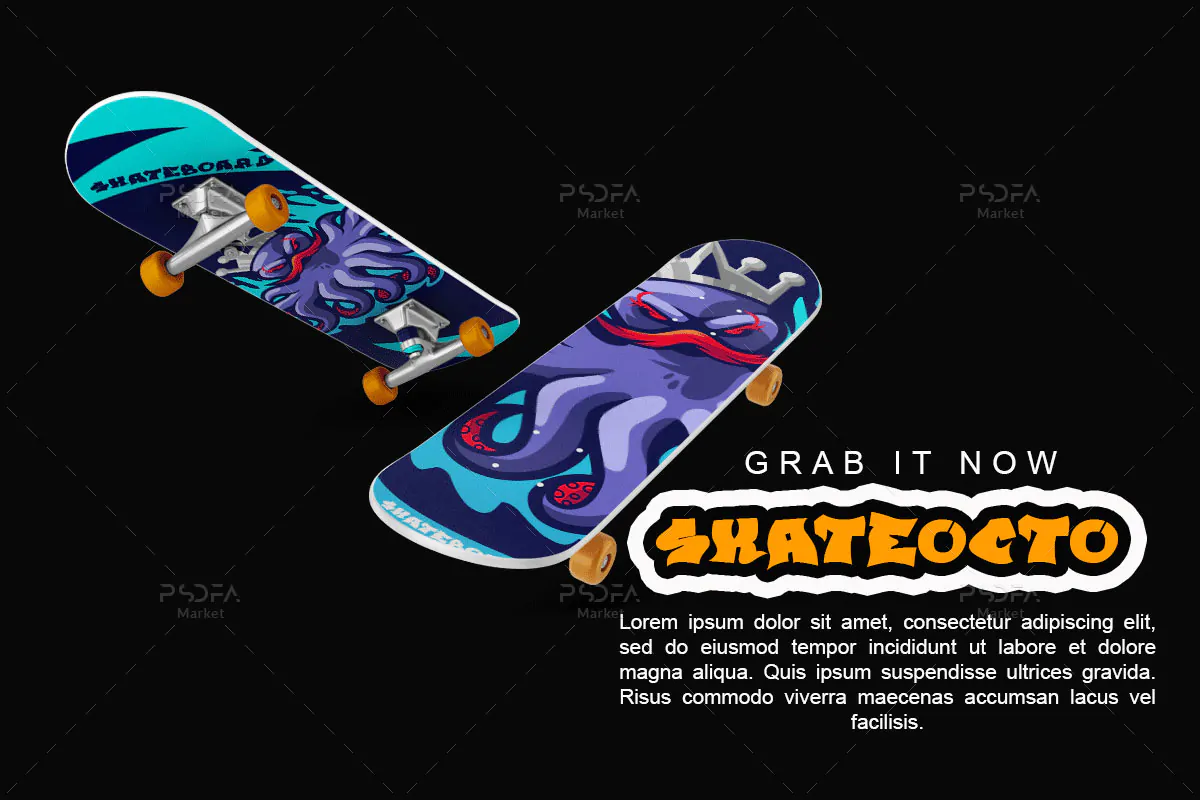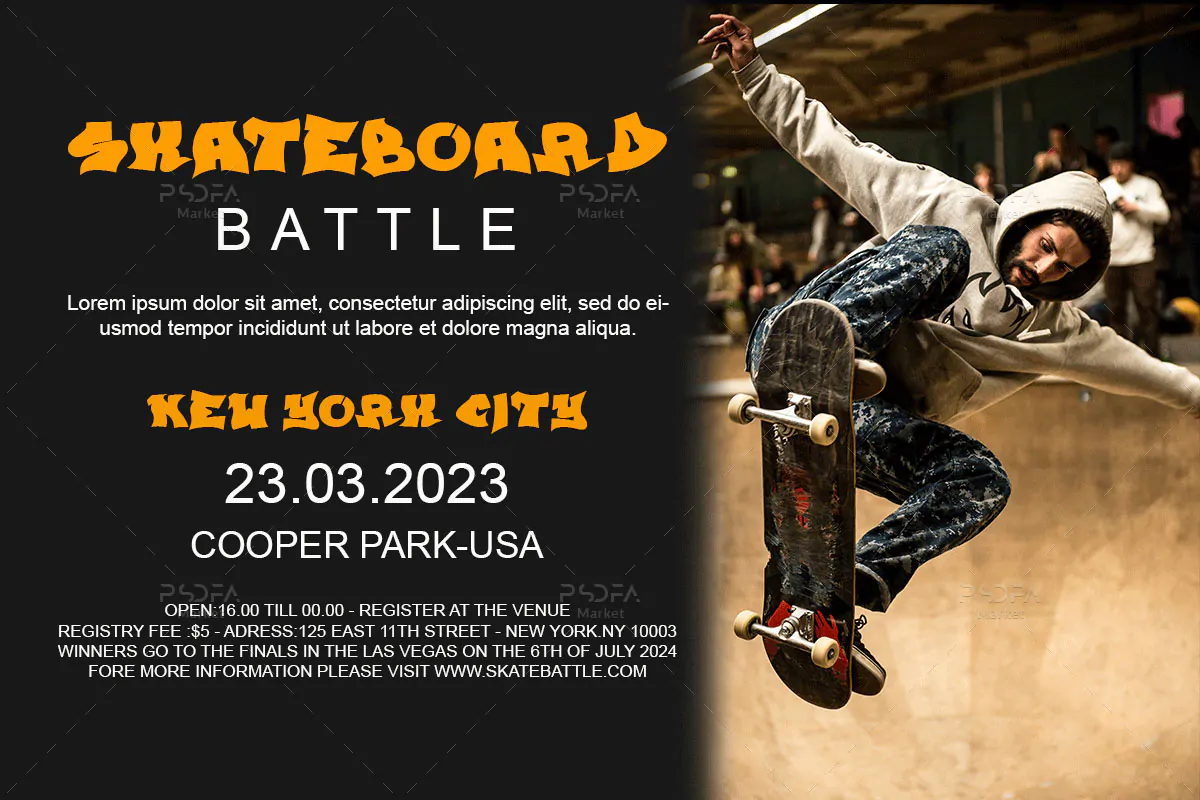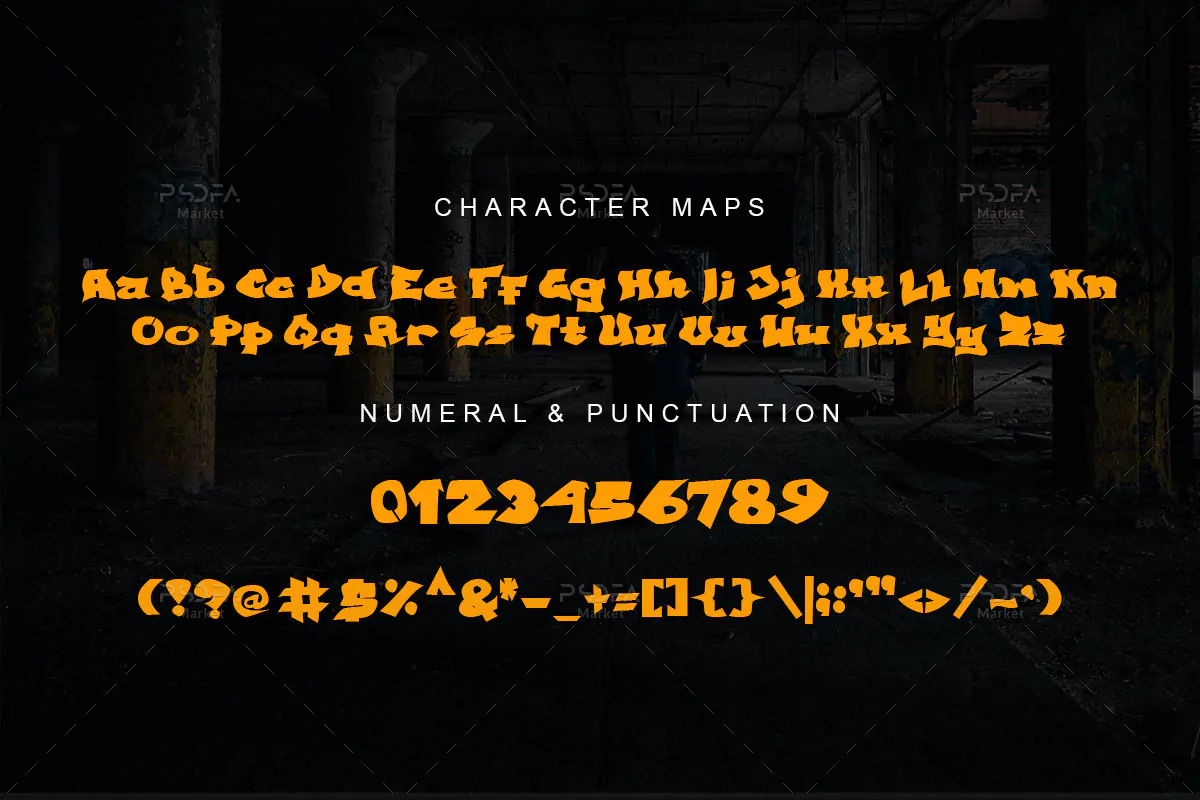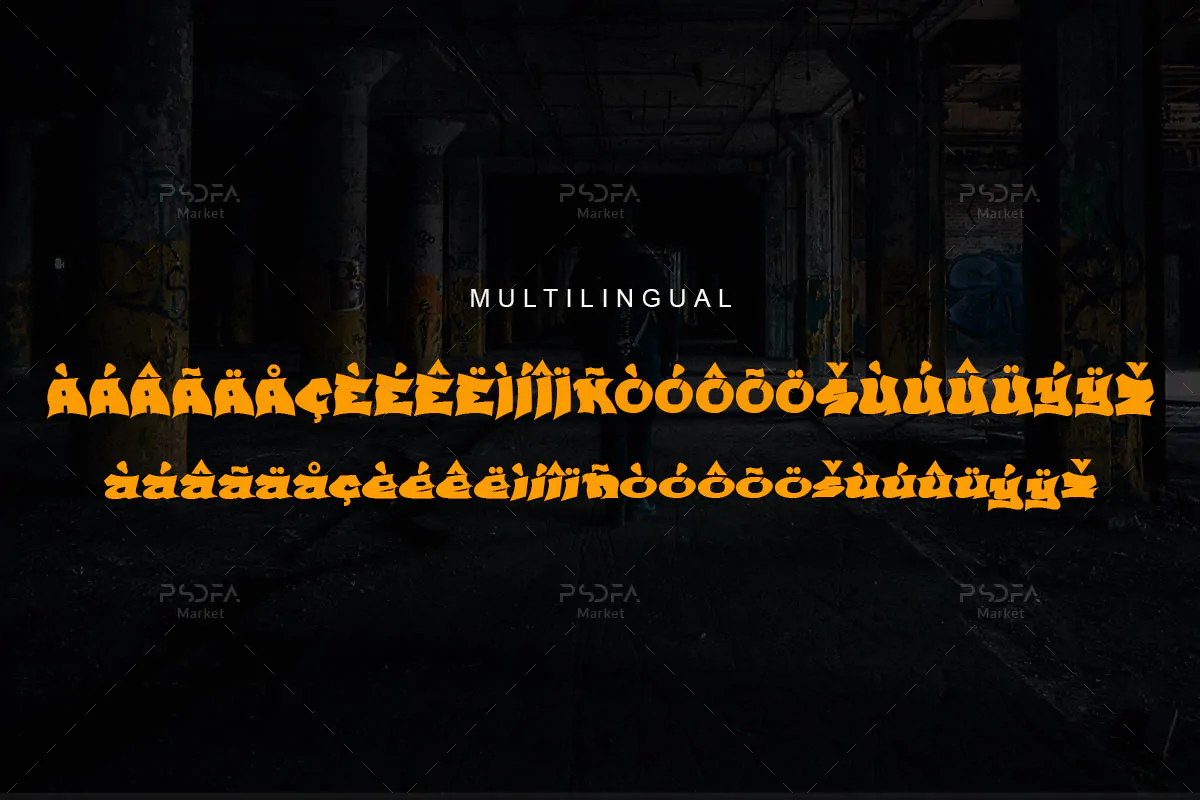
فونت گرافیتی ضخیم و بولد Willy
فونت گرافیتی ضخیم
فونت گرافیتی ضخیم و بولد Willy یک قلم نمایشی فوق العاده زیبای انگلیسی است که به سبک طرح نوشتههای دیواری طراحی شده است و مناسب جهت استفاده در طرحهای گرافیکی مختلف میباشد. فونت Willy با وزن معمولی طراحی شده است که میتوانید از آن در طراحی انواع پوستر، لوگو، کارت ویزیت، تراکت، بسته بندی محصولات، ظروف یکبار مصرف، چاپ تیشرت و … استفاده کنید.